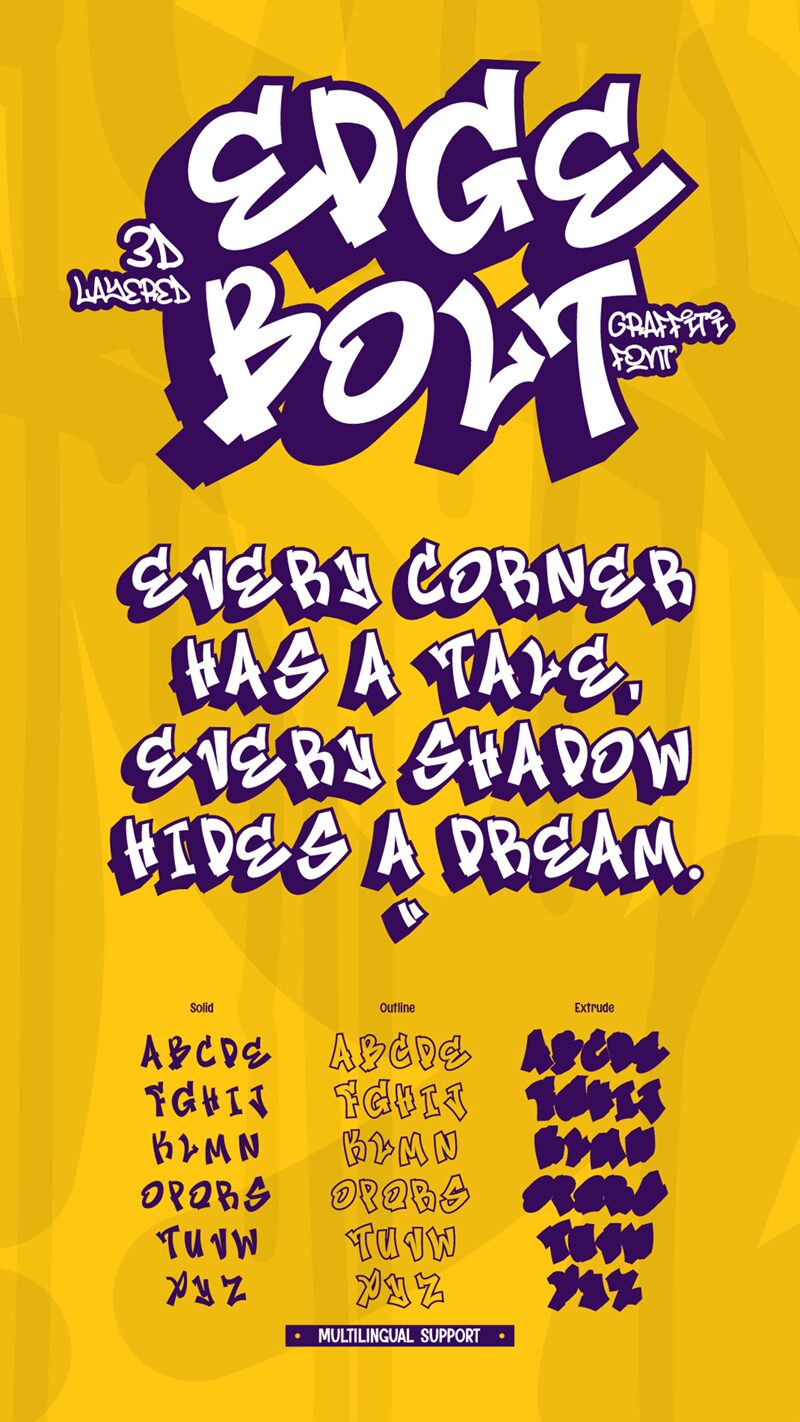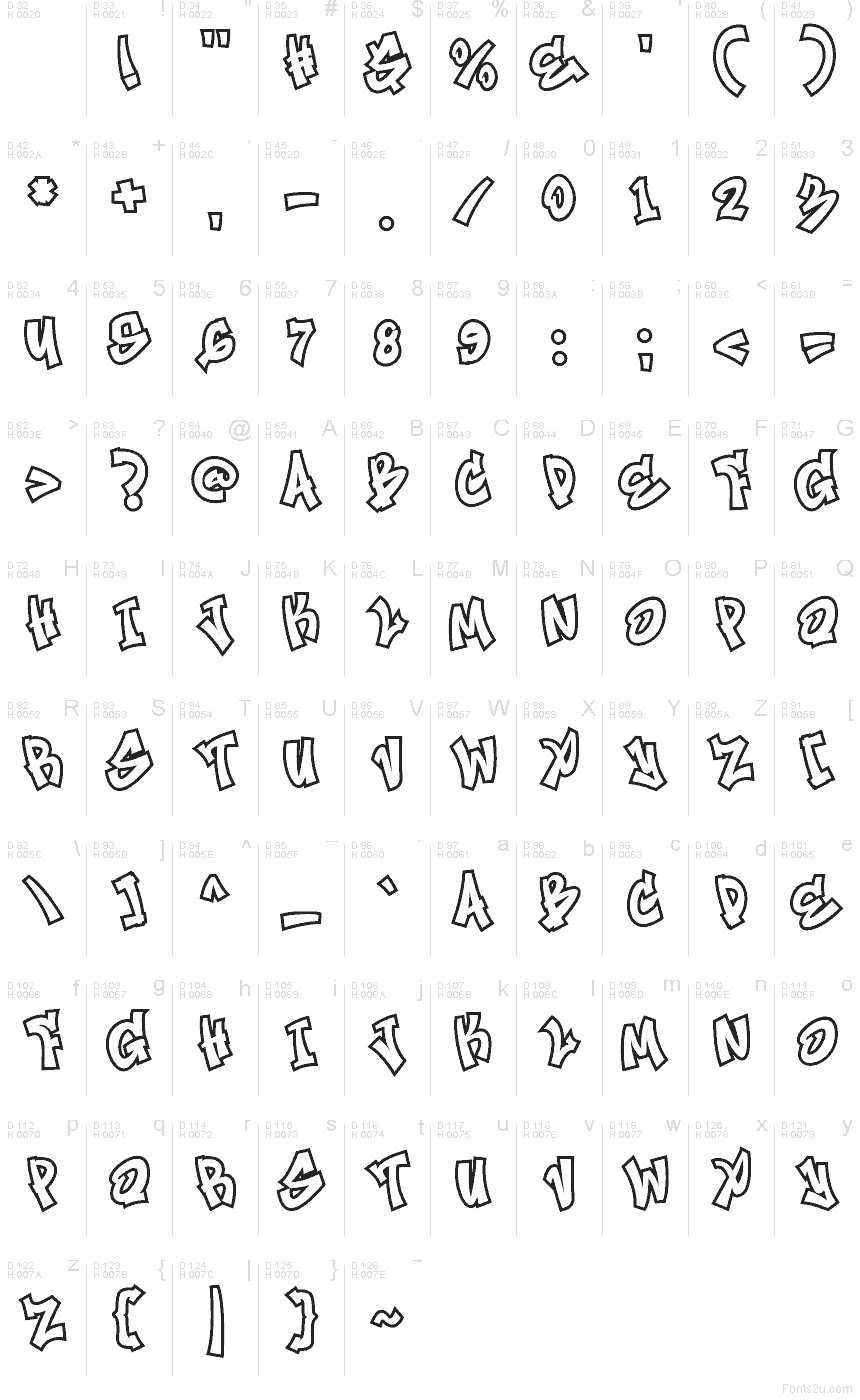
Písmo Edge Bolt Outline od Muhammada Panji Ramdhaniho z Figuree Studio pochází z rodiny Edge Bolt. Jde o bezplatné graffiti písmo s úderným obrysem připomínajícím samolepku. Působí dojmem ručního nástřiku, ale je precizně vykreslené. Robustní a hravé tvary v kombinaci s těsným rytmem dodávají slovům výraznou siluetu bez nutnosti vyplňovat vnitřek znaků – vaše sdělení tak zůstává vzdušné, ostré a snadno vrstvitelné přes rušná pozadí. Písmo si zachovává pouliční postoj, ale nabízí dostatečnou čitelnost pro rychlé vnímání.
Vyzkoušejte Edge Bolt Outline na grafice pro skateboard a streetwear, hudebních plakátech, náhledech videí na YouTube, brandingu e-sportových týmů, obalech alb, letácích na akce a výrazných nadpisech na merchandisingu. Toto bezplatné písmo vynikne také při vrstvení barev nebo umístění přes fotografie – přidejte za něj tučnou výplň nebo stín pro okamžitou hloubku. Pro hlavní text jej kombinujte s jednoduchým neo-groteskním bezpatkovým písmem a Edge Bolt Outline použijte ve velké velikosti, aby měl obrys prostor dýchat.